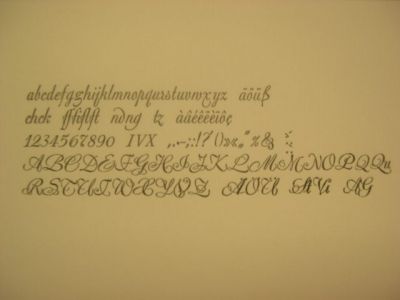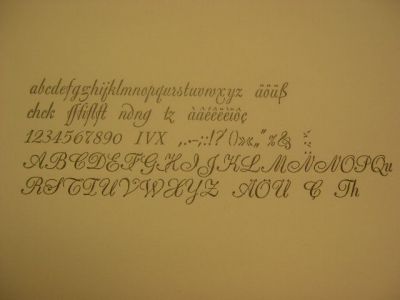
Ein Sommernachtstraum - Schrift gesucht, Bild vorhanden
Welche Schrift wurde da auf der Internetseite der Landesbühne Hannover verwendet? Finde keine Schrift mit einem ähnlichen S...
Schau Dir mal die Virtuosa I an:
D.Stempel AG, Frankfurt am Main
Erstguß 1951
Entwurf Hermann Zapf
Interessant dabei: Die Virtuosa II wurde von Hermann Zapf erst vier Jahre später, im Jahr 1955, auf Wunsch der Schriftgießerei entworfen. Normalerweise gibt es zunächt die Grundversion, aus der dann vielleicht einmal zusätzliche Zier-Versalien geschaffen werden. Hier ist es genau anders herum gelaufen. Die Gemeinen, Ziffern und Punkturen sind identisch. Nur die Versalien der Virtuosa II sind schlichter.
Die Schrift sieht mir die Bickham Script Pro von Adobe sehr ähnlich. Linotypes Shelly Script oder die ITC Edwardian Script könnte sehr gut sein.